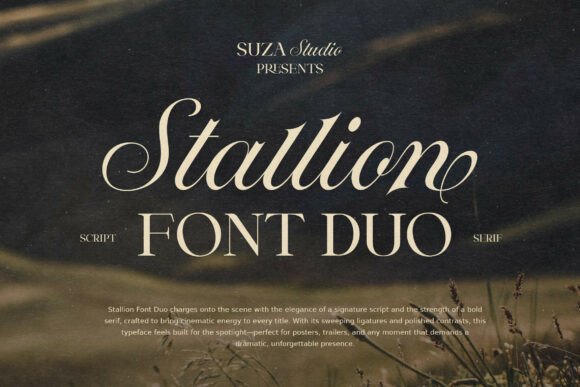
Stallion Duo
Trouver les bons éléments de conception peut être un défi, mais Stallion Duo propose une collection exceptionnelle qui rehausse instantanément votre travail.